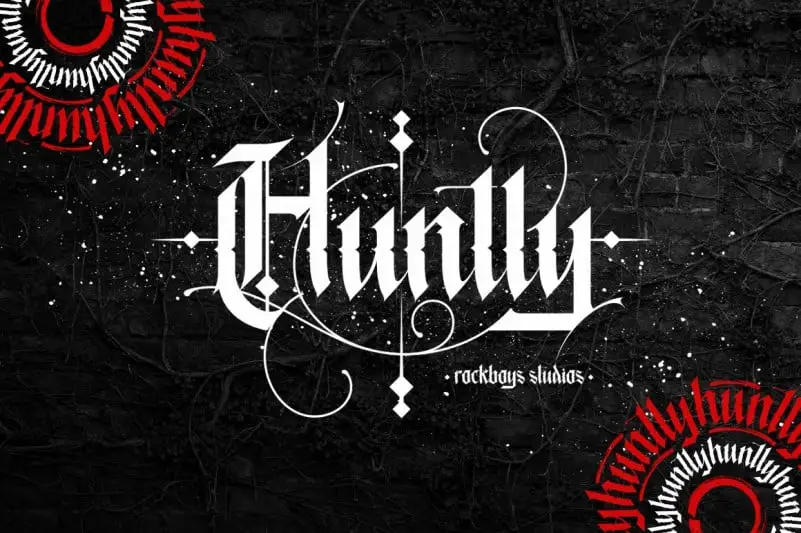
Huntly Blackletter Font – Download Grátis
Aqui está uma descrição curta e envolvente para a página de download da fonte Huntly Blackletter Font: Descubra a tradição artística da era vitoriana com o Huntly Blackletter Font, inspirado no estilo robusto e elegante dos anos 1800. Esta fonte romana curvada oferece uma paleta única para títulos de capitalizadas variadas e alternativas para alterar os caracteres, tornando-a perfeita para projetos vintage. Perfeito para logotipos, selos, artefatos, revistas e outros materiais gráficos que buscam um toque antigo e sofisticado. Com as opções de alternativa para o gíria único e personalizável de cada letra maiúscula, este font se destaca como uma escolha inovadora. O Huntly Blackletter Font tem a capacidade de transformar seus projetos em verdadeiras obras-primas que representam sua marca ou projeto de forma autêntica e única. Este é um recurso gráfico ideal para quem busca algo distintivo, sofisticado e vintage sem sair da página. Mantenha-se acima das demais com o Huntly Blackletter Font, uma fonte curvada romana perfeita tanto para os mais experientes quanto para aqueles que estão começando em design de gráficos.